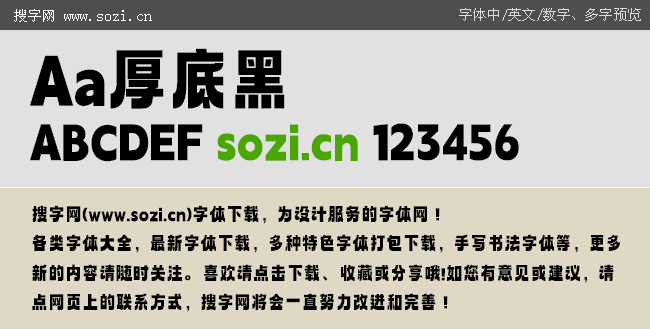
Aa厚底黑
搜字網給大家提供一款Aa厚底黑中文字體下載,Aa厚底黑是一款藝術黑體字體,字體筆畫橫粗豎細,與傳統(tǒng)的字體有較大不同。在字型上,用了弧度比較大的曲線讓字體更活潑一些,已覆蓋GB2312規(guī)范的6763字。具有很好的視覺感。Aa厚底黑允許任何個人與企業(yè)免費使用,包括全媒體商用用途,無需取得任何書面授權,但禁止任何違法用途。